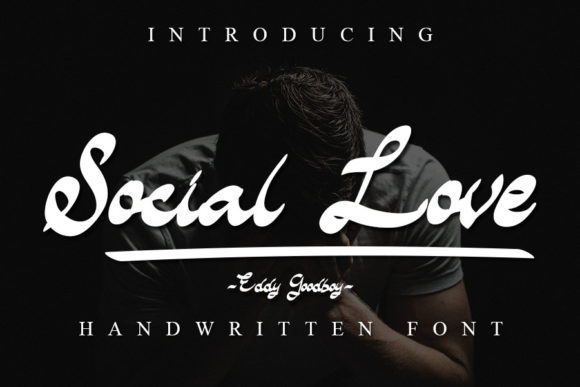
Creativefabrica Social Love Font
[Creativefabrica] Social Love Font
Social Love - шикарный, изысканный шрифт, излучающий утонченность и элегантность.
Стильные чередования и лигатуры делают этот шрифт идеальным для любого проекта.